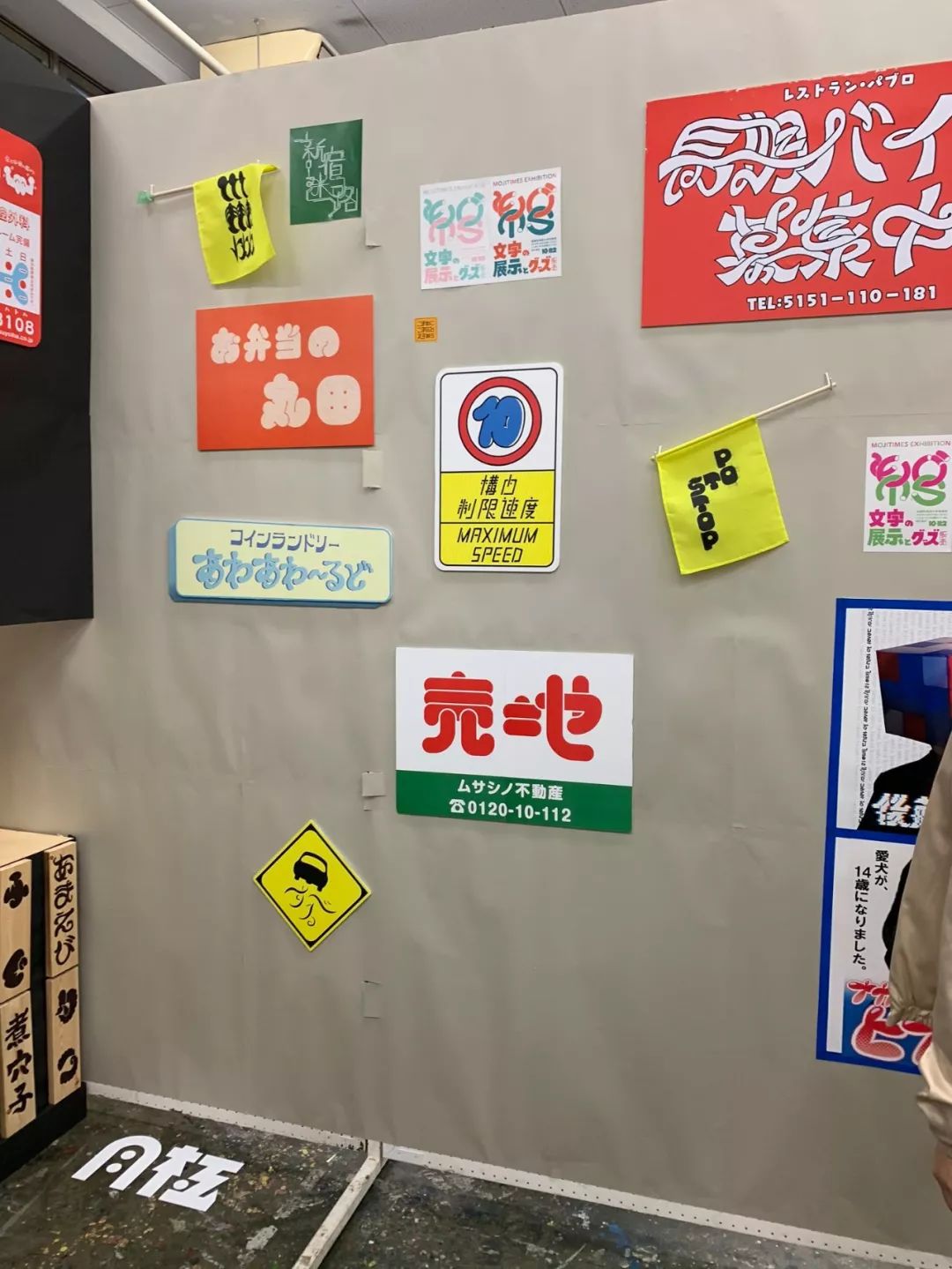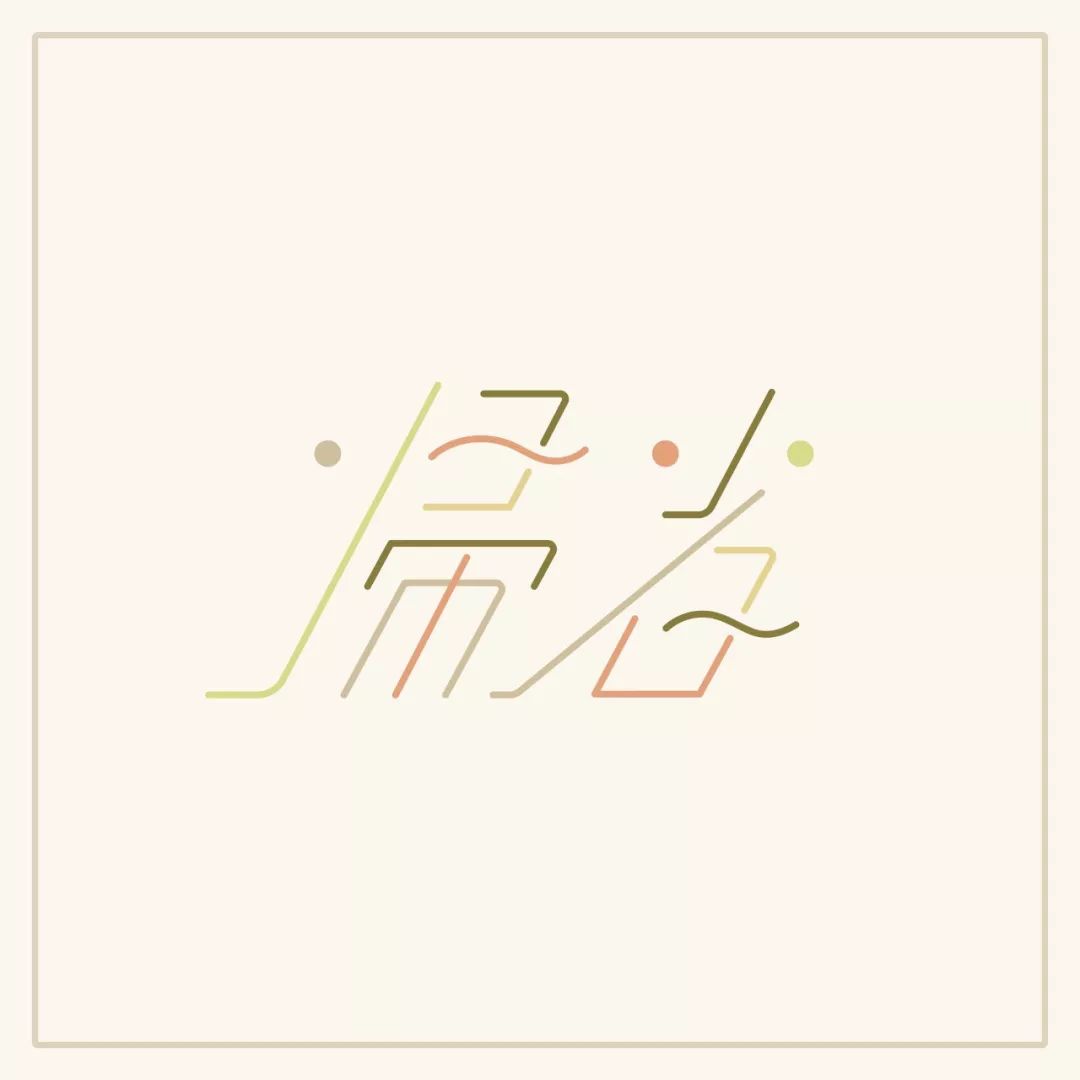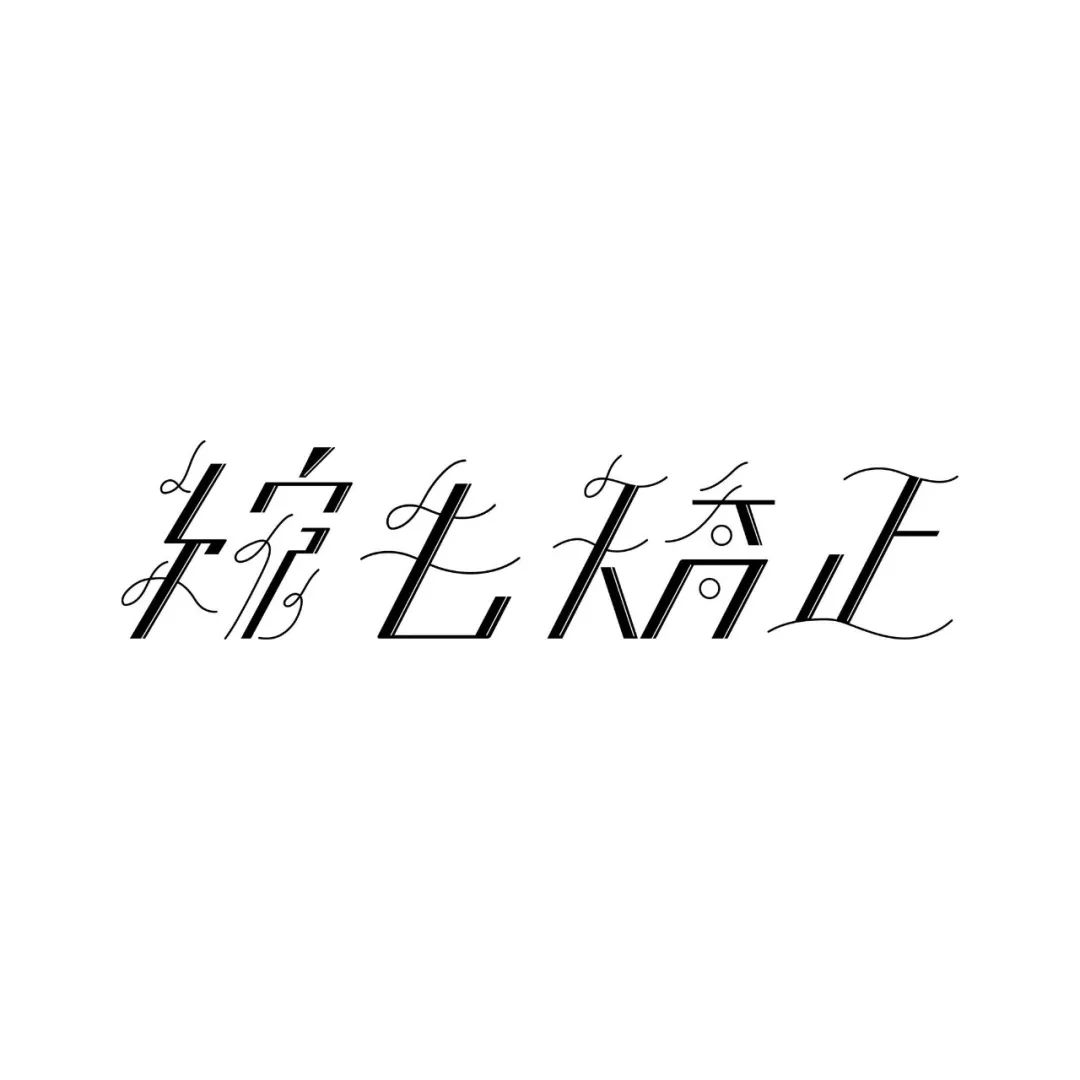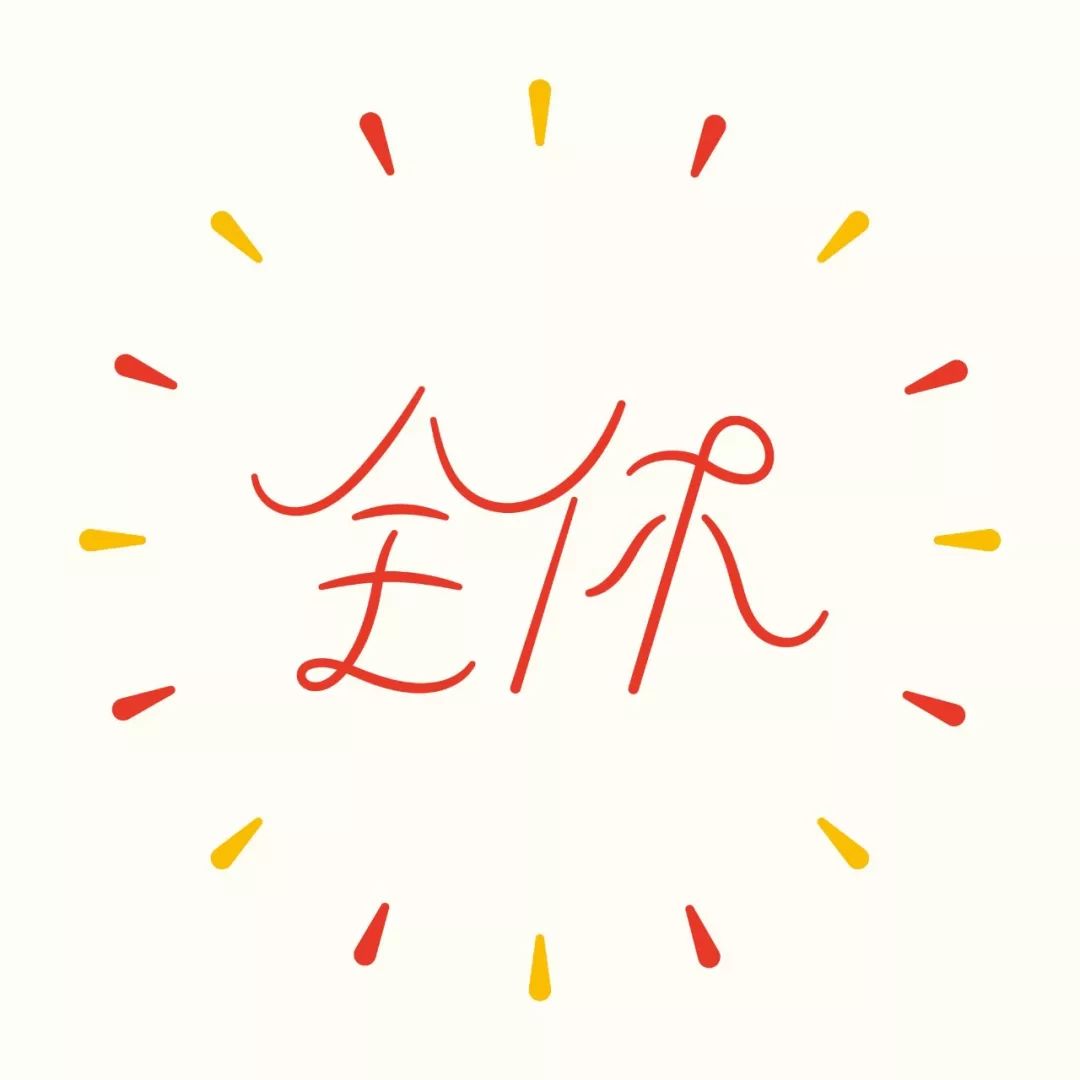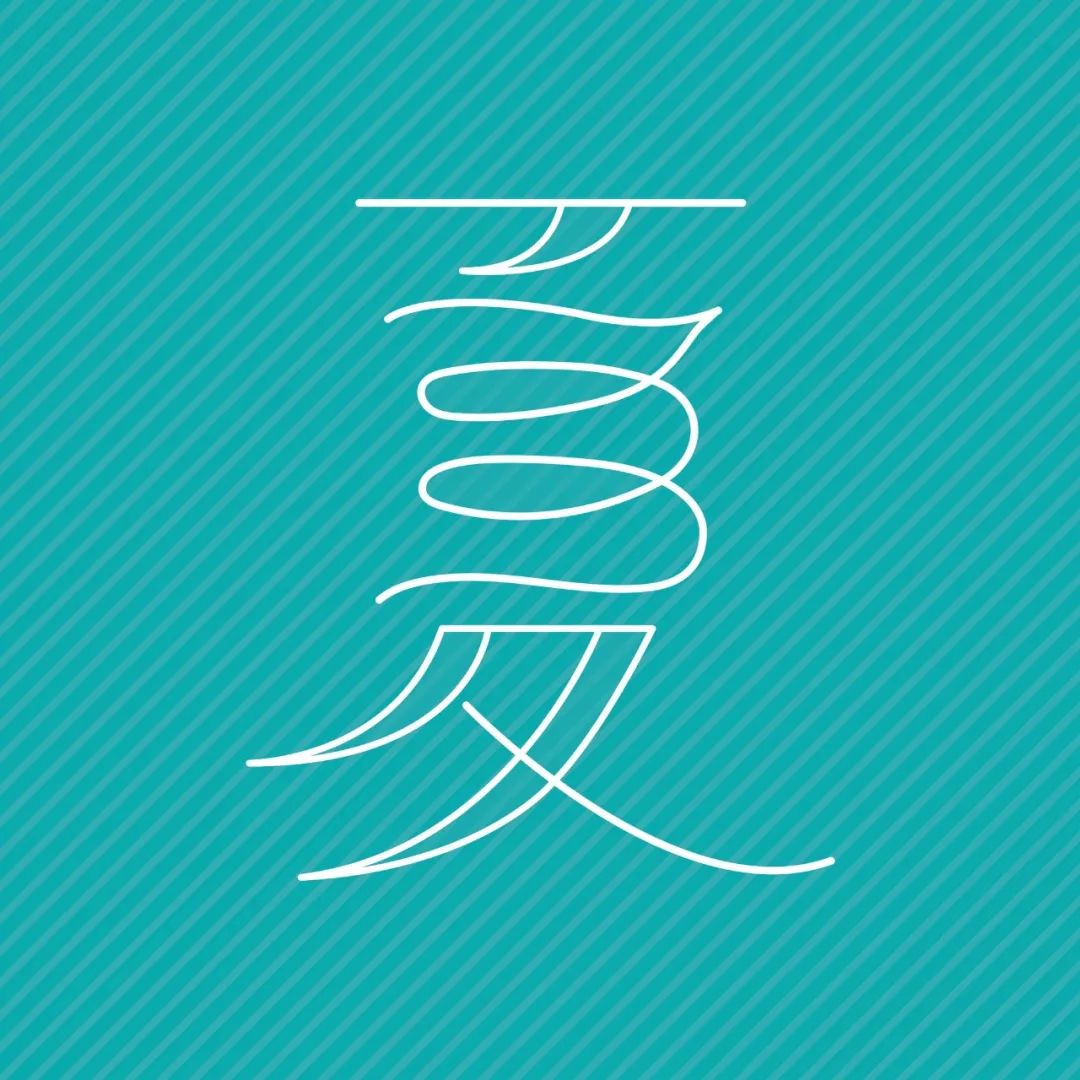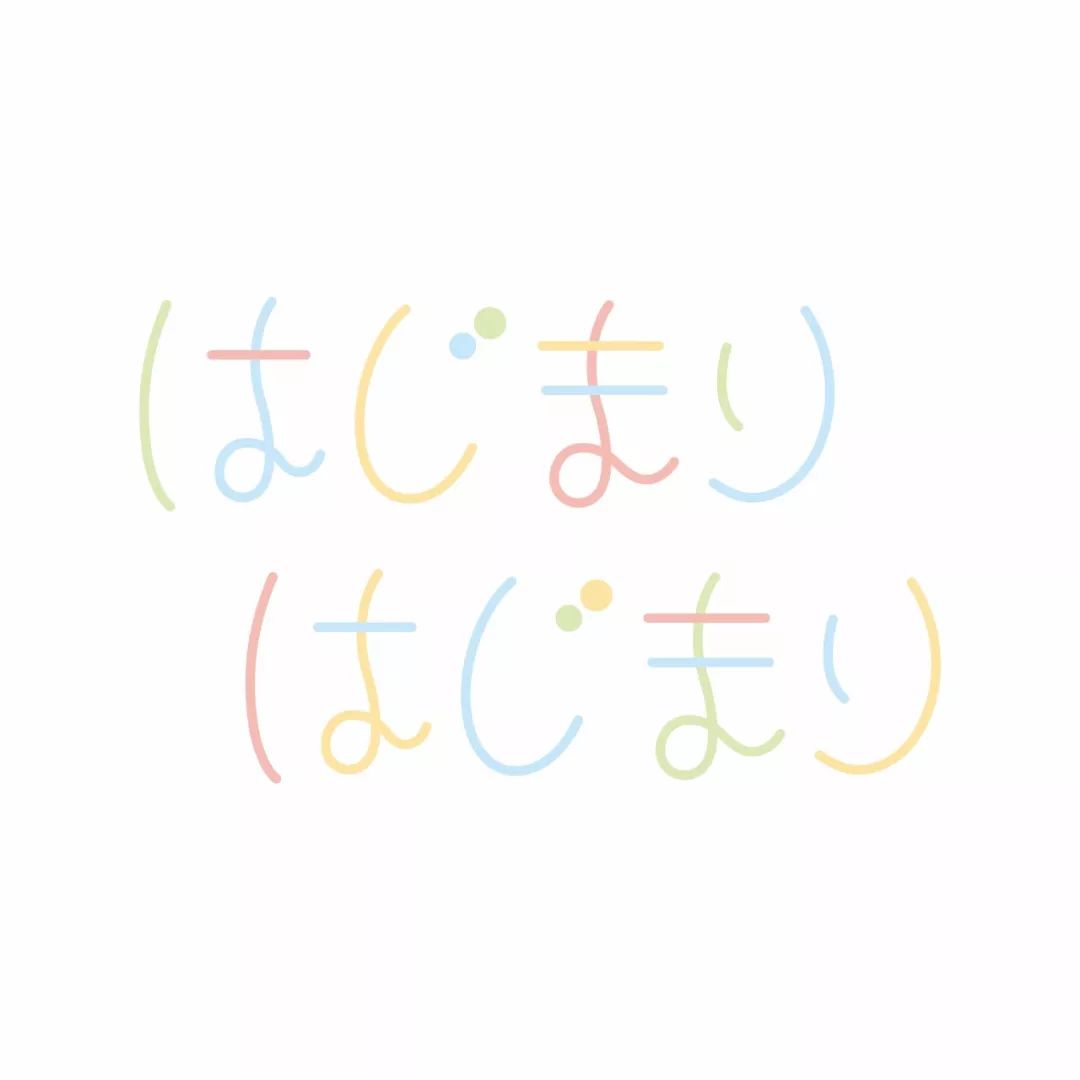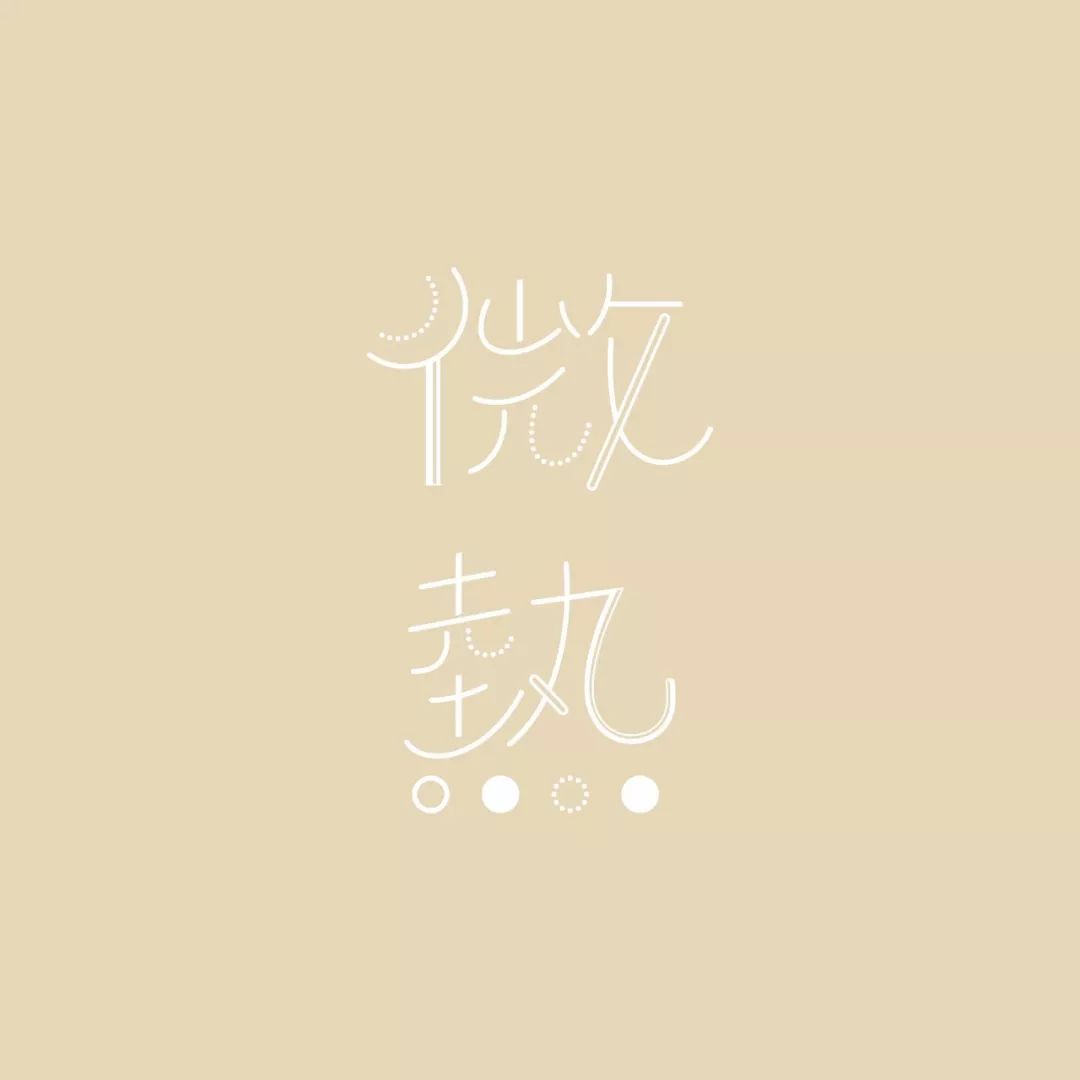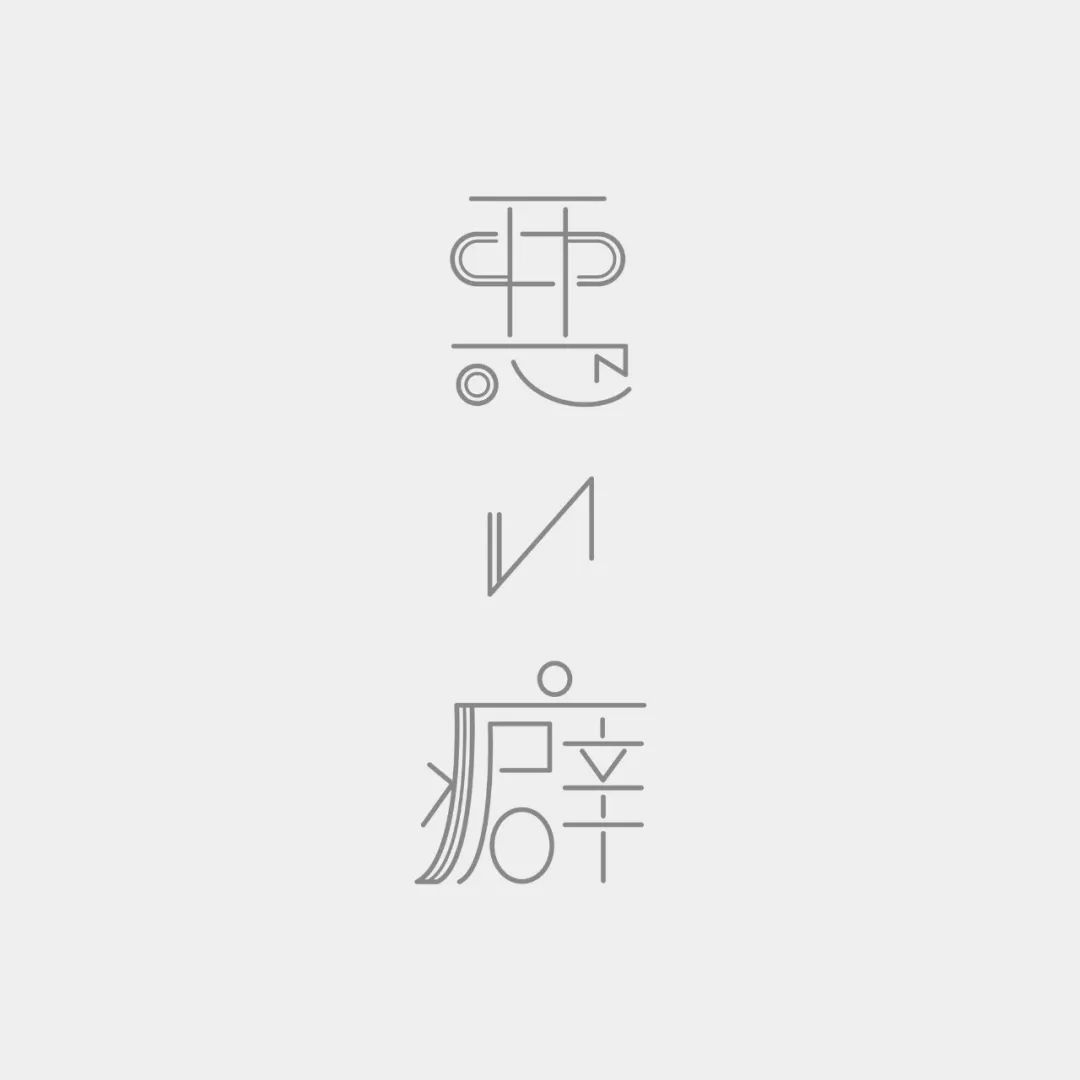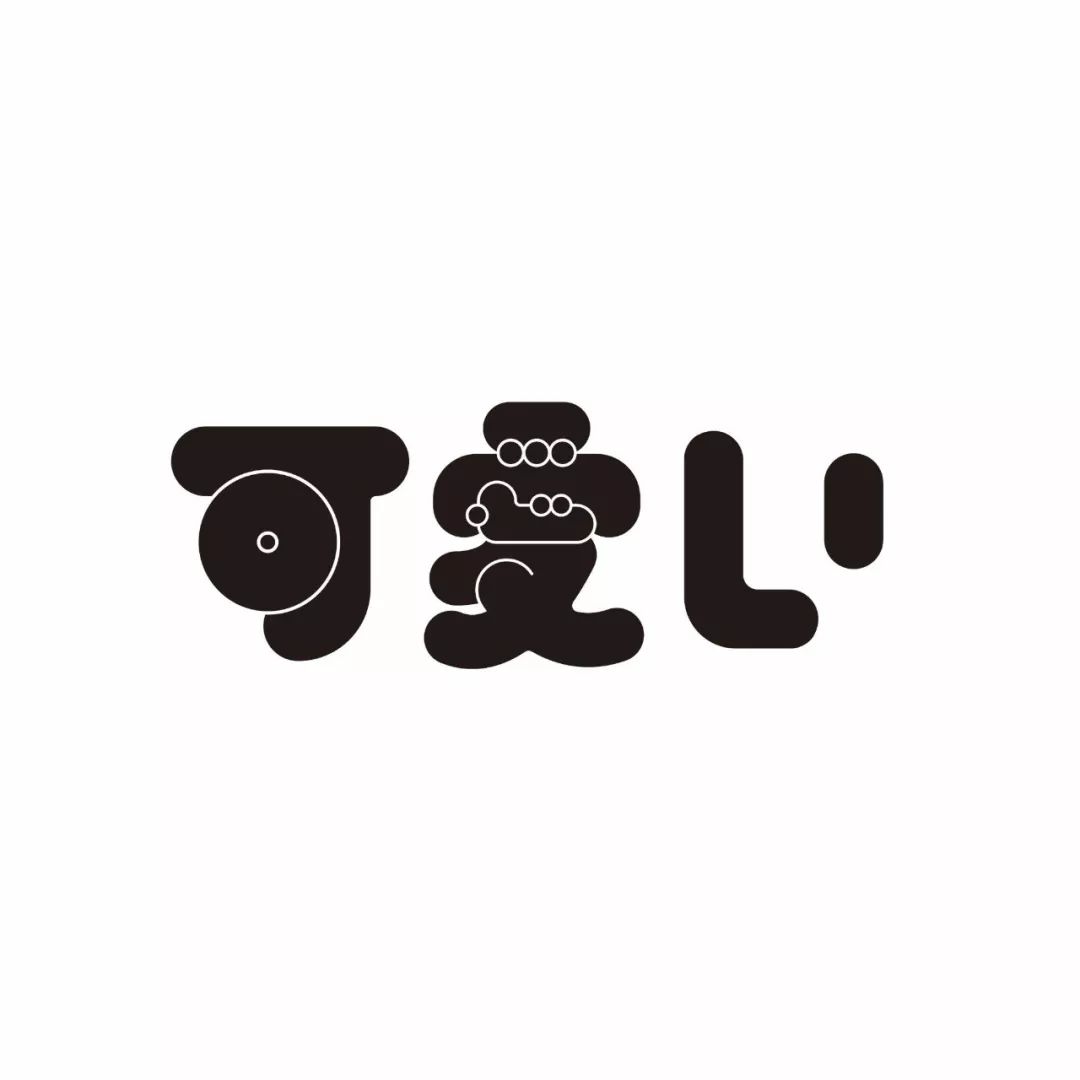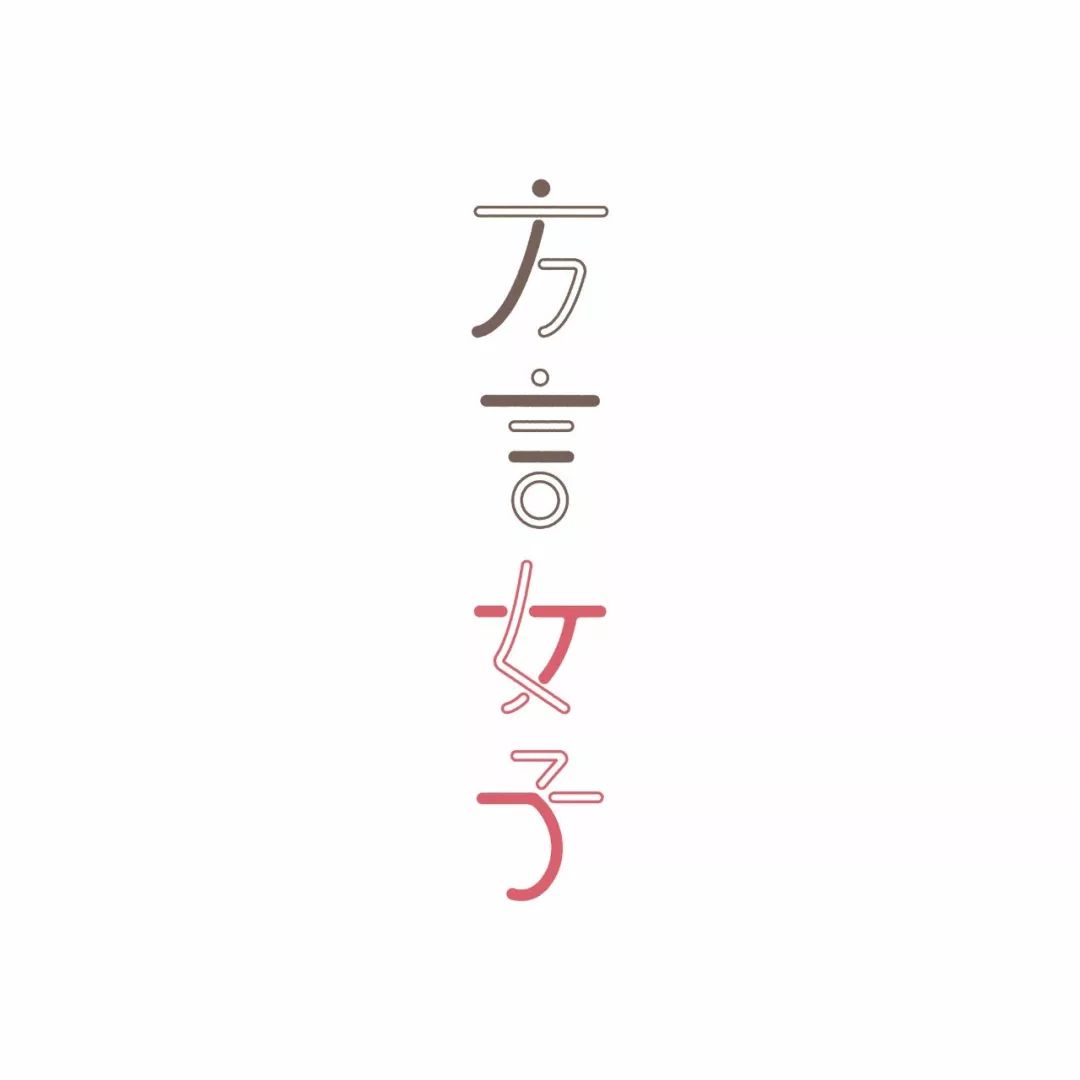
日本这位20岁的字体设计师,来认识一下
ひなこ
一位来自日本的设计师
据说目前仅有20岁
他的字体设计挺有意思的
通过字体设计记录日常生活
今天和大家通过作品来认识一下他
10月底
在武蔵美芸術祭『もじTIMES』的展览
下面
和大家看看他的一些实验性字体作品
全休
物欲
夏が過ぎてく
20岁生日的设计“诞生日”
yonige / 春の嵐
帰省
现在头发很光滑
设计了上面的这个字体
大家明白是什么意思吗
这个时期头发乱成一团
夏
可愛い
悪い癖
方言女子
微熱
太
戀
参作
目前
ひなこ 坚持以字体设计的形式
记录自己的日常
专注于做好一件事情